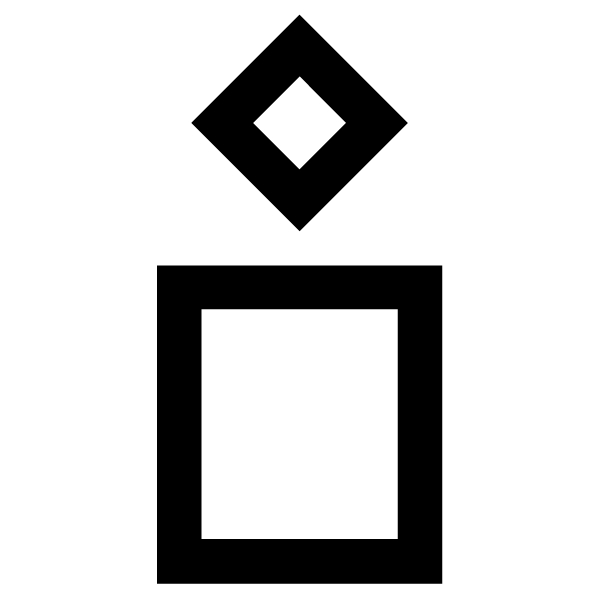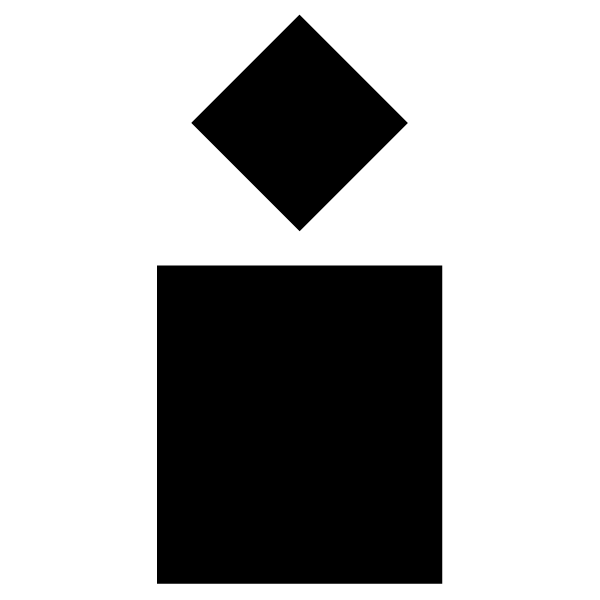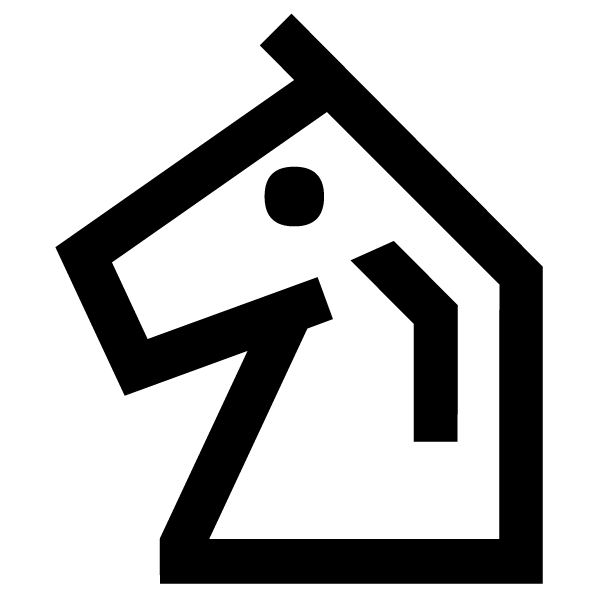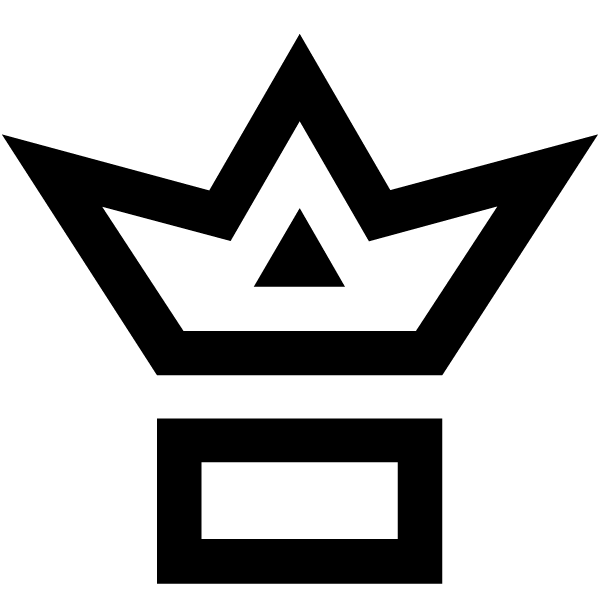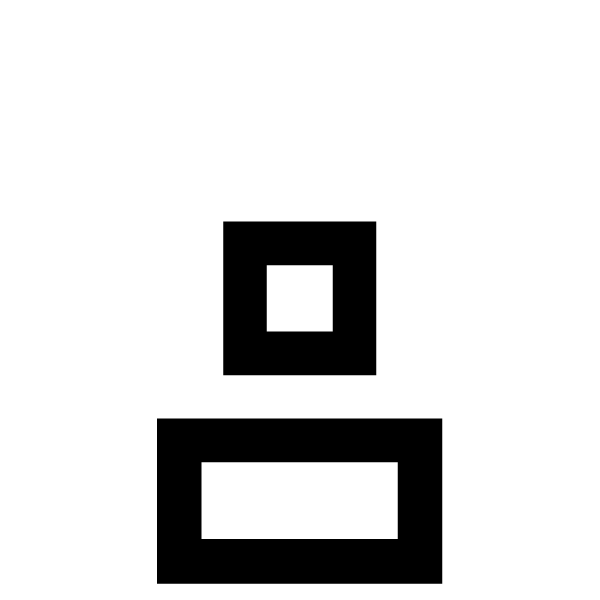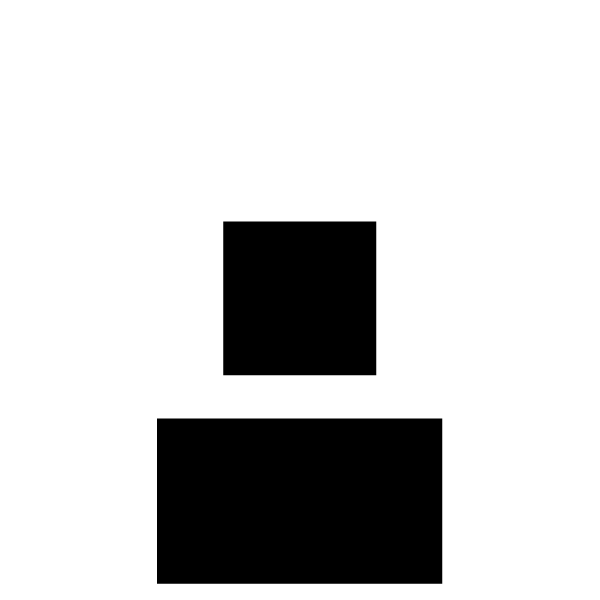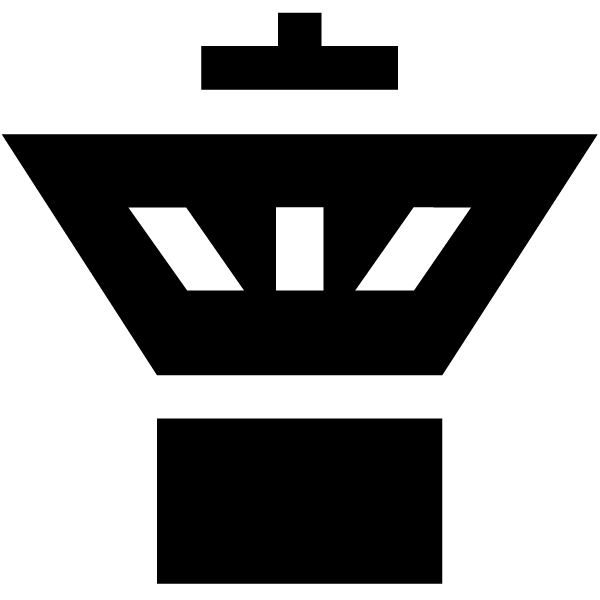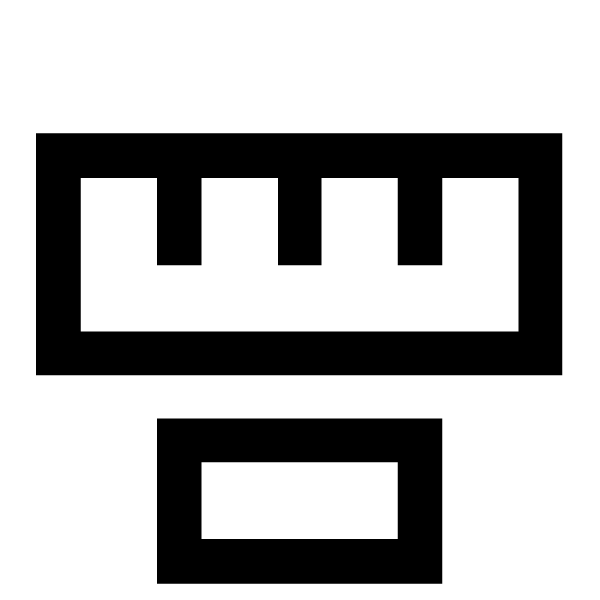
La Fuente Chess Line es un diseño de ajedrez con un estilo minimalista y moderno, caracterizado por sus piezas cuadrangulares y el distintivo diseño del caballo. Creada por Armando Hernandez Marroquin, esta fuente es una excelente opción para quienes buscan un toque estético y funcional en proyectos de diseño gráfico, documentos o tableros digitales de ajedrez.
Juego de Ajedrez con la Fuente Line: